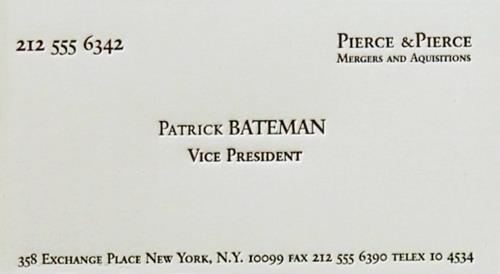
Ist Euch eigentlich mal aufgefallen, wie schlecht Batemans Visitenkarte wirklich ist?
Für diejenigen, die den Film, die Szene nicht kennen:
Also ein fehlendes Leerzeichen, nicht gesperrte Versalien, eine nicht gegliederte Fußzeile, ... Ich hätte das dem Drucker wieder in die Hand gedrückt und gesagt, das wäre mir peinlich...
Oja, das ist mir gar nicht aufgefallen! Lustig sind die Schriftnamen übrigens schon. Sollte ich jemals eine Schrift benennen müssen, hätte ich eine Inspirationsquelle :)
Und Visitenkartenkarton mit Wasserzeichen ist auch Bullshit, weil Karton ab einer bestimmten Stärke halt mehr oder weniger völlig opak ist.
Gesehen auf Spiegel Online:
… in „Lumpenschrift“ :hammer:
Arme Frakturfreunde! :schonklar: :schonklar:
Immerhin Catfonts’ Digitalisierung der Mainzer Fraktur und nicht meine, wenn ich das richtig sehe.
Da ich gerade einen Artikel über den Dada-Künstler Hugo Ball am Wickel habe, bin ich auf zwei typografisch interessante Bilder bei wikipedia gestoßen. Die minimalistische Todesanzeige aus der Zeitschrift De Stijl:
Und die in der Schriftauswahl sehr reichhaltige Ausgabe des Lautgedichtes "Karawane" von 1917:
Und Visitenkartenkarton mit Wasserzeichen ist auch Bullshit, weil Karton ab einer bestimmten Stärke halt mehr oder weniger völlig opak ist.
Dachte ich auch, bis ich Waterford-Bütten-Karton in die Hand bekam. Wasserzeichen bis 640g/qm, allerdings nur an einem Rand des Rohbogens in 560 x 760 mm. Um völlig lichtundurchlässig zu sein, muß ein weißer Karton schon viel dicker sein. Und die Jungs in dem Film mit den schlechten Visitenkarten haben sicherlich nicht mehr als 300g/qm in der Hand.
Was mich in diesem Zusammenhang mal interessiert (und ja vielleicht auch die Film-Fritzen):
Was in etwa hätten die (außer der Nennung im Nachspann) auf den Tisch legen müssen, hätte man für so eine Filmszene wirklich einen Satz von "Boh-Wow!-Visitenkarten in Einzelanfertigung angefertigt?
(wobei ich fast annehme, dass die Visitenkarten in diesem Fall als Kontrast zu den Prahlern ganz bewusst eher grottenschlecht sind)
Ja, aber nur so in etwa Pi x Daumen, nur die ungefähre Größenordnung.
Kann ja sein, dass so etwas für einen Film mal wieder gebraucht wird, und die dann wirklich was gutes zeigen wollen. Dass da dann ein weitere Raum nach beiden Seiten bleibt ist klar.
Ich habe so etwas schon gemacht für Filme. Der letzte Auftraggeber hat eine Karte mit gleichem Text und unterschiedlichen Entwürfen im Abstand von zwei Wochen zweimal zum vollen Preis drucken lassen von jeweils etwa 200 Euro netto + MWSt. inkl. Entwürfe und Satz. Die Auflage betrug 20 Stück, und es wurden drei unterschiedliche Papiere eingesetzt. Eine höhere, normale Auflage hätte nur unwesentlich mehr gekostet.
Na, so etwas sollte ja problemlos in das Film-Budget rein passen.
Dann kann man das auch für solch einen Zweck mal ordentlich machen. Und  klar, das größte am Preis ist ja Satz- und Rüstkosten.
Sind euch eigentlich schon die lustigen Anführungszeichen aus den neuen Bild-Werbespots aufgefallen?
Ich dachte zuerst, das wäre ein Fehler, aber meines Wissens gibt es ja gar kein doppeltes unteres 66-Anführungszeichen, oder?
Trotzdem etwas befremdlich, Worte wie kompetent mit Anführungszeichen zu relativieren. :neenee:
Aber als Zitat aus was, von wem? Naja, vielleicht hast du recht; ich habe aber trotzdem immer ein komisches Gefühl, wenn ich solche Schlagwörter in Anführungszeichen sehe.
Ist jetzt zwar nicht derselbe Fall, aber ich las mal in einer Speisekarte:
Wiener Schnitzel-Art, „paniert“
:hammer:
Die verbindende Klammer scheint zu sein, daß man dem Aberglauben anhängt, Anführungen könne man als eine Art Betonungszeichen einsetzen.
Ihr habt zwar recht, dass es hier wohl Zitat-Anführungszeichen sein sollen, nicht dass einer denkt, die eine Person sei die vielseitige, und die andere sei kompetent. Trotzdem hat man ja gerade bei der Bild eine Anführungszeichen-Tradition, und sie war auch nicht all zu selten in etwa so "kompetent" wie die "DDR" demokratisch und in der Sicht der Bild überhaupt ein Staat war.
Aber vielleicht hat man ja auch einen speziellen Anführungsstriche-Code: 66/99 klammert ein, und verstärkt, 99/66 hingegen klammert aus, und relativert?
im context mit der bild verstehe ich das allerdings eher so das diese begriffe als zitat ja auch zur zeitung passen sollen.
kompetent in bezug auf falsche anführung ist leider alles andere als kompetent, das erwarte ich bei der bild aber auch nicht. ich frage mich nur wieso die das machen, ästhetik?
ich glaube auch das thema mit den 6699-anführungen hatten wir hier auch schonmal, es gibt wohl einige die das sinnvoller empfinden als 9966.